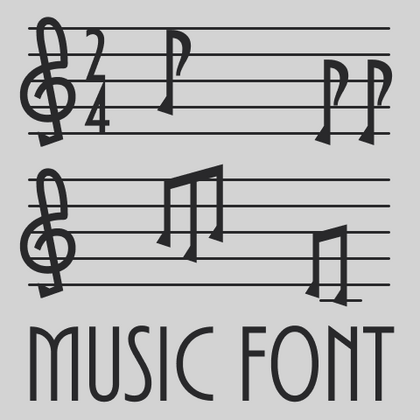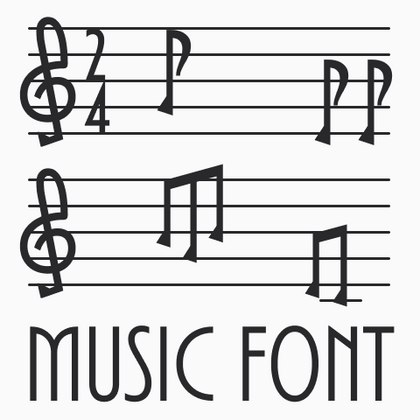
Музыкальные шрифты
Для создания запоминающихся афиш и обложек требуются музыкальные шрифты, где дизайн каждой буквы отражает характер звука. Их отличают динамичные формы, ритмичные пропорции и элементы. В коллекции TypeType представлены как смелые акцидентные шрифты, так и утонченные каллиграфические варианты — все они передают энергию и настроение музыки через типографику.
TT Glips — экспериментальный моноширинный гротеск с рукотворным характером. В маленьком кегле он кажется технологичным, но при увеличении размера проявляет округлые детали и мягкие формы.
TT Odellia — старостильная антиква с современным рисунком, вдохновлённая венецианскими шрифтами и классической музыкой.
TT Nooks Script — шрифт с уникальным рисунком, который не имеет прямых аналогов.
TT Rationalist — функциональный и оригинальный брусковый шрифт с актуальным рисунком. Он универсален и подходит как для заголовков, так и для массивов текста.
TT Bells сочетает в себе элегантную мягкость антиквы с непростым и дерзким характером, который выражается в прямых срезах и клинообразных засечках. В основе шрифта лежит ширококонечное перо, характерное для старостильных шрифтов, создающее эти атмосферные срезы и засечки.
TT Turns — геометрический гротеск с акцентными круглыми знаками и выразительными нависающими элементами. Это универсальный шрифт, который лаконично выглядит и отлично читается в маленьком размере, при этом в крупных кеглях становится акцидентным и проявляет свой характер на максимум. Он энергичный, сильный и динамичный — особенно отчётливо это проявляется в наклонных начертаниях.
TT Regins — шотландская новостильная антиква с королевским характером. Яркий контраст и острые треугольные засечки придают этому шрифту строгий и властный нрав.
В TT Frantz можно найти небольшие отсылки в эстетике арт-деко, которые выражены в сильно заниженной или наоборот сильно завышенной талии у букв. Кроме того, в зависимости от положения ползунка регулировки оси, у некоторых букв изменяется закрытость апертуры.
TT Quaris — изысканная и современная ленточная антиква. Перед разработкой этой гарнитуры мы провели глубокое исследование архетипов ленточных антикв.
TT Ricordi Allegria — современная ленточная антиква, отличительные особенности которой, гиперболизированная разноширинность в пропорциях, контраст между штрихами, клиновидные окончания штрихов и отсутствие традиционных засечек.
TT Norms® Pro — один из самых востребованных шрифтов студии, выбор известных мировых брендов. Более трёх переизданий за семь лет, первые строчки на MyFonts, десятки кастомизаций. Это «рабочая лошадка», которая станет незаменимой базой любой шрифтовой коллекции.
TT Commons™ Pro — один из самых востребованных шрифтов студии. Сфера его применения практически безгранична! Беспроигрышный вариант для тех, кто ищет стильный и функциональный базовый шрифт для любых проектов.
TT Hoves Pro — скандинавский гротеск с нейтральным, но в то же время узнаваемым характером. Это удобный и функциональный, при этом стильный и эстетичный инструмент для дизайнеров. Такой шрифт позволит вам решать множество разноплановых задач!
TT Supermolot Neue — непобедимое оружие в борьбе за стиль! Это технологичный модульный гротеск с футуристическим настроением и мощным функционалом. Шрифт идеально подойдёт для оформления компьютерных игр и множества других проектов.
TT Firs Neue — сбалансированный гротеск со скандинавскими мотивами. Это выразительный и привлекательный, при этом лаконичный и универсальный в использовании шрифт. Переиздан дважды, чтобы быть безупречным.
TT Rounds Neue — мягкий и дружелюбный шрифт, который умеет быть разным. В тонких начертаниях он выглядит минималистично и нейтрально. В жирных же — «надувается» и округляется, приобретая инфантильные черты.
TT Fors — тот самый шрифт «для всего». Это стильный, лаконичный и функциональный геометрический гротеск с выверенными формами. Его можно использовать и в интерфейсах, и для создания акцентов.
TT Ramillas — стильная и современная антиква, которая украсит любой проект. Уникальные декоративные начертания и буквицы с цветочным орнаментом помогут создать неповторимый дизайн. Шрифт уже используется на 3000+ сайтах во всем мире, а также отмечен наградой Modern Cyrillic.
TT Biersal — акцидентный гротеск со свободным, озорным и авантюрным характером. Отправной точкой для его создания послужил немецкий плакат начала 30-х годов. Мы хотели сохранить не только пропорции, но и ощущение небрежности, живости леттеринга из референса.
TT Paplane — акцидентный сквадраченный гротеск. Так, характерные черты этого гротеска — сквадраченные формы, 45-градусные срезы и обтекаемые внешние контуры.
TT Tricks — современная текстовая антиква, дизайн которой отсылает к стилю переходных антикв. Это шрифт со спокойным, элегантным и в меру строгим характером.